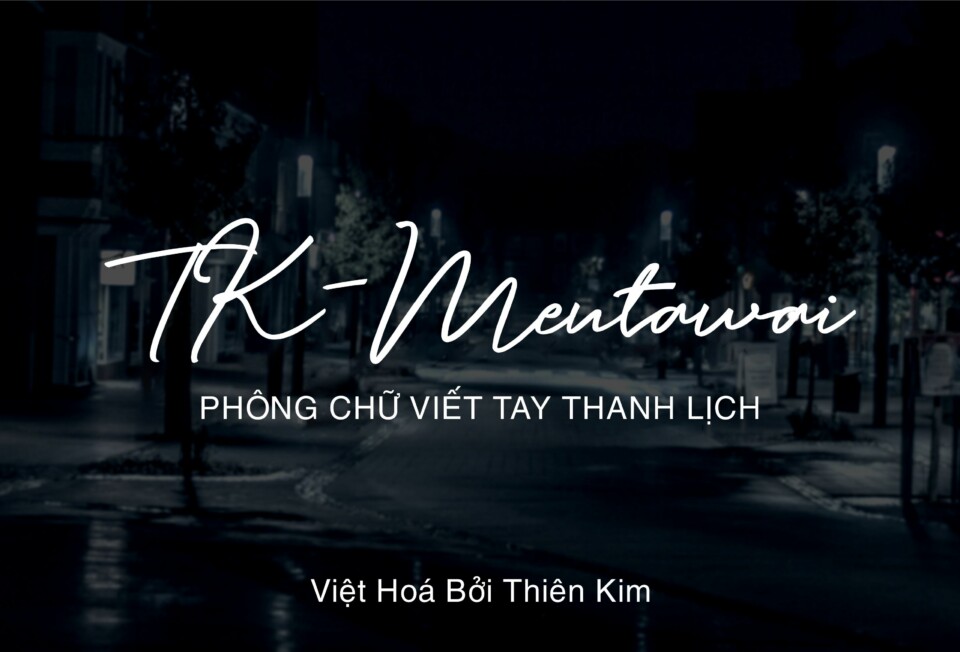
Tải Font Việt Hoá TK-Mentawai Miễn Phí Cho Thiết Kế Sáng Tạo
Giới thiệu về bộ Font Việt Hoá TK-Mentawai
Trong thế giới thiết kế đồ họa hiện đại, việc tìm kiếm một bộ Font Chữ độc đáo và đầy cá tính luôn là ưu tiên hàng đầu của các nhà sáng tạo. Font Việt Hoá TK-Mentawai chính là giải pháp hoàn hảo mang đến sự kết hợp tinh tế giữa nét đẹp hoang sơ tự nhiên và phong cách thiết kế đương đại. Được lấy cảm hứng từ những đường nét thủ công, bộ phông chữ này giúp các tác phẩm của bạn trở nên sống động, gần gũi nhưng không kém phần chuyên nghiệp.
Đặc điểm nổi bật của Font Việt Hoá TK-Mentawai
Điểm ấn tượng nhất của Font Việt Hoá TK-Mentawai chính là sự linh hoạt trong ứng dụng. Bộ font đã được tối ưu hóa hoàn toàn bảng mã tiếng Việt, giúp người dùng dễ dàng gõ các ký tự có dấu mà không lo lỗi hiển thị. Với các đường nét thanh mảnh xen lẫn những chi tiết phá cách, đây là lựa chọn lý tưởng cho các dự án thiết kế bìa sách, poster sự kiện trường học hoặc các bài thuyết trình sáng tạo của học sinh và sinh viên.
Ứng dụng thực tế của Font Việt Hoá TK-Mentawai trong thiết kế
Người dùng có thể sử dụng bộ font này cho nhiều mục đích khác nhau. Trong giáo dục, giáo viên có thể dùng để trang trí bài giảng điện tử thêm phần sinh động. Trong truyền thông, các designer thường dùng Font Việt Hoá TK-Mentawai để làm nổi bật tiêu đề quảng cáo hoặc thiết kế nhận diện thương hiệu thủ công. Khả năng tương thích tốt trên các phần mềm như Photoshop, AI hay Canva giúp bộ font này trở nên cực kỳ phổ biến.